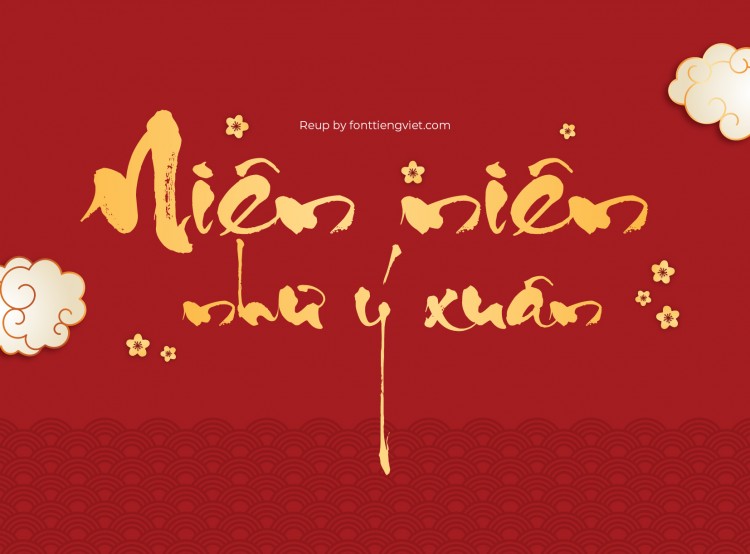
Font Thư Pháp Quang Ninh (2 font) – Tết: Nét Chữ Việt Cho Mùa Xuân Đoàn Viên
Giới thiệu về bộ Font Thư Pháp Quang Ninh (2 font) – Tết
Trong không khí rộn ràng của những ngày cuối năm, việc tìm kiếm một bộ Font Chữ ấn tượng để thiết kế thiệp chúc mừng hay bao lì xì là điều rất cần thiết. Font Thư Pháp Quang Ninh (2 font) – Tết chính là lựa chọn hoàn hảo dành cho những ai yêu thích vẻ đẹp truyền thống pha lẫn nét hiện đại. Bộ font này không chỉ mang lại giá trị thẩm mỹ cao mà còn giúp truyền tải trọn vẹn hồn cốt của thư pháp Việt Nam vào các tác phẩm kỹ thuật số một cách tinh tế và đầy cảm xúc.
Đặc điểm nổi bật của Font Thư Pháp Quang Ninh
Bộ Font Thư Pháp Quang Ninh (2 font) – Tết bao gồm hai biến thể khác nhau, giúp người dùng linh hoạt trong việc sáng tạo. Điểm đặc trưng của bộ chữ này là các nét bút mềm mại, uyển chuyển nhưng vẫn giữ được sự mạnh mẽ, dứt khoát như được viết bởi những ông đồ thực thụ. Với khả năng hỗ trợ tiếng Việt hoàn chỉnh, bạn sẽ không gặp bất kỳ lỗi hiển thị nào khi gõ các dấu thanh phức tạp trên máy tính.
Ứng dụng Font Thư Pháp Quang Ninh (2 font) – Tết trong thiết kế
Nhờ thiết kế mang đậm tính nghệ thuật, Font Thư Pháp Quang Ninh (2 font) – Tết cực kỳ phù hợp cho các dự án liên quan đến lễ hội và văn hóa. Bạn có thể sử dụng font để thiết kế tiêu đề cho các banner sự kiện, trang trí câu đối đỏ hay làm nổi bật những lời chúc ý nghĩa trên mạng xã hội. Sự kết hợp giữa hai phông chữ trong cùng một bộ giúp tạo nên sự tương phản thú vị, giúp bố cục thiết kế trở nên hài hòa và chuyên nghiệp hơn.
Lưu ý khi sử dụng font thư pháp
Mặc dù bộ font rất đẹp, người dùng nên chú ý điều chỉnh khoảng cách giữa các chữ cái để đạt được hiệu quả thị giác tốt nhất. Việc sử dụng màu sắc vàng hoặc đỏ sẽ càng làm tôn lên vẻ đẹp sang trọng của bộ chữ này trong ngày Tết.
Kết luận về bộ font thư pháp miễn phí